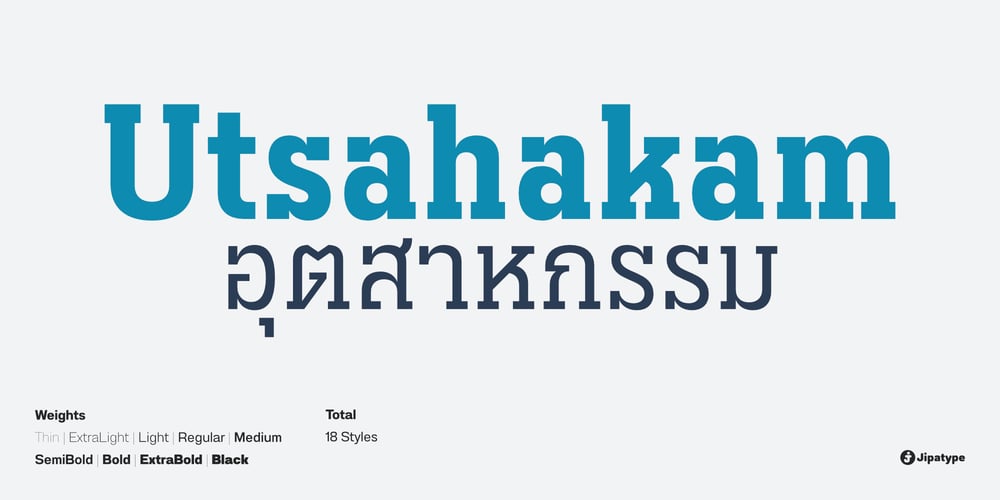
Utsahakam Font Family was designed by Anupap Jaichumnan and published by Jipatype. Utsahakam contains 18 styles and family package options. ฟอนต์อุตสาหกรรม เป็นอักษรแบบสลับเซอริฟ ที่มีแข็งแกร่ง หนักแน่น มั่นคง มีทั้งหมด 9 น้ำหนักและตัวเอียงของแต่ละน้ำหนักรวมทั้งหมดมี 18 สไตล์ รองรับหลากหลายภาษา เหมาะสำหรับการใช้ผาดหัว ป้าย ข้อความโปรยสั่นๆ ฟอนต์อุตสาหกรรมสามารถช่วยส่งเสริมมูทแอนโทนให้ดูหนักแน่น มั่นคง น่าเชื่อถือ เหมาะกับสินค้าและบริการที่เกี่ยวข้องกับ เครื่องจักร, โรงงานการผลิต, เครื่องมือช่าง หรืออุตสาหกรรมหนักUtsahakam is a slab serif typeface look strong, solid, stable. Comes with 9 weights and italics of each weight total 18 styles. Support multi-languages. Suitable for headline or sub-headline. Utsahakam can help you to create a mood and tone of strong, solid, stable and reliable. For a product and service about machine, manufacturing factory, mechanic tools or heavy industry.